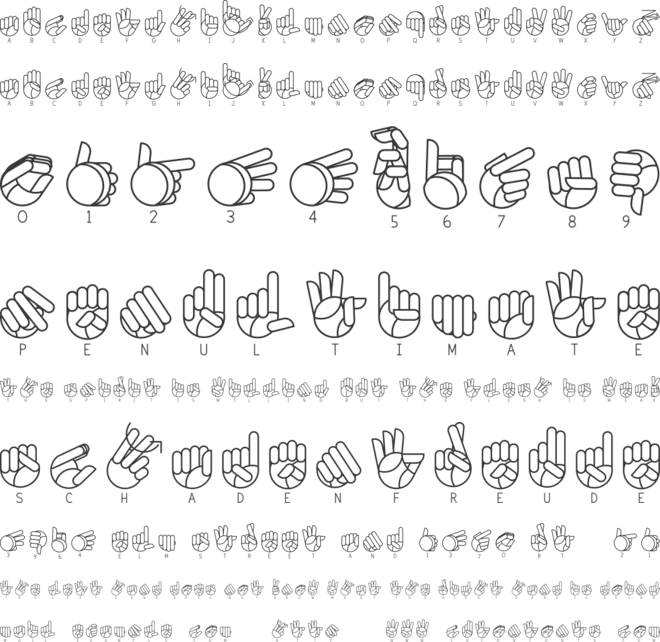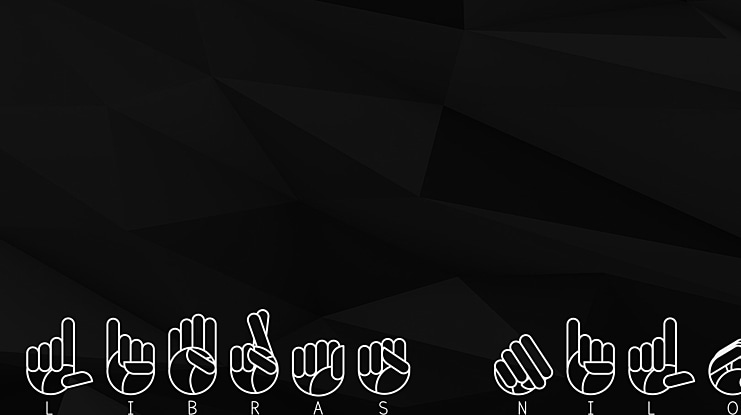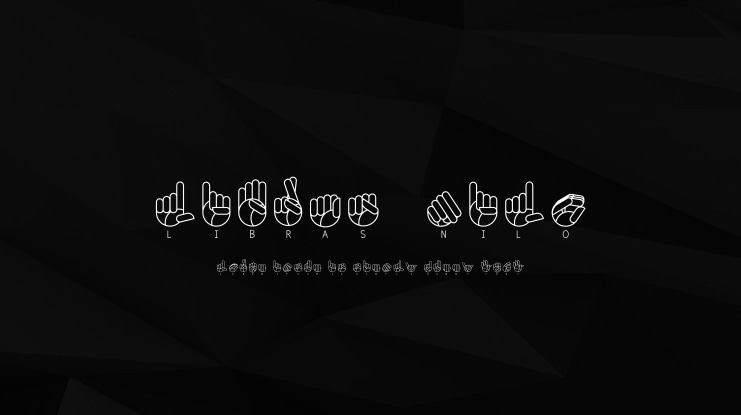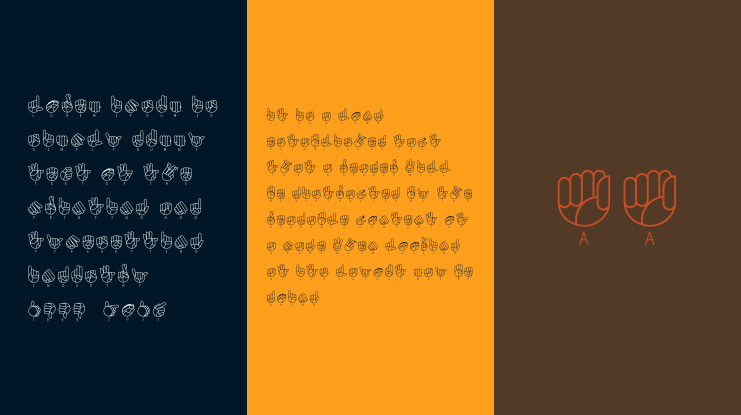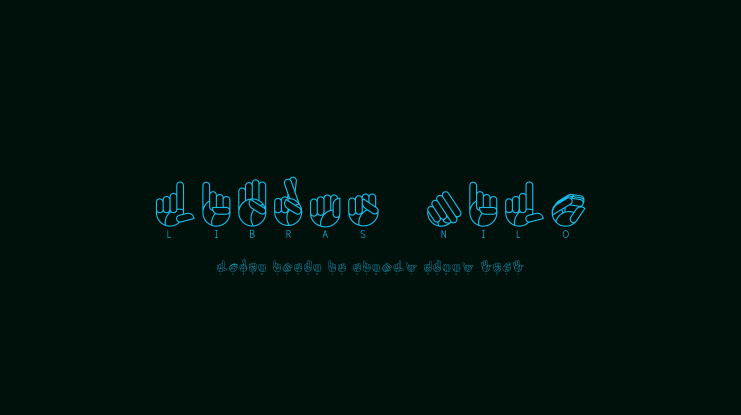
Libras-nilo Font Family
Tipografia Ilustrada em Libras (sigla de Língua Brasileira de Sinais), um conjunto de formas gestuais utilizado por deficientes auditivos para a comunicação entre eles e outras pessoas, sejam elas surdas ou ouvintes.